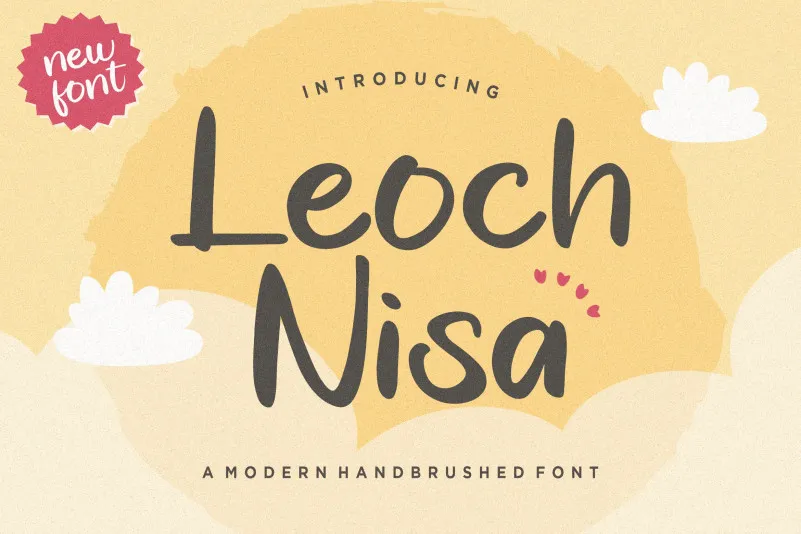
Leoch Nisa Font – Fonte Grátis
Leoch Nisa Font
A Leoch Nisa é uma bela fonte Brush Font que se destaca pela sua elegância moderna e acabamento brincalhão. Ideal para diversos tipos de aplicação, esta fonte pode ser usada com sucesso no design de casamentos, projetos de marca, logotipos, cartazes, cartões de nome, convites, posts em redes sociais, e muito mais. Com uma aparência sofisticada que mistura modernidade com um toque de naturalidade, a Leoch Nisa traz para seus trabalhos um toque único e chamativo. Seja você um designer de casamentos buscando algo novo e criativo para suas designs, ou simplesmente alguém que está procurando uma fonte divertida e elegante para seus projetos em geral – é certamente o tipo de font que você precisa. Suavemente branca sobre qualquer fundo, esta font permite que seus trabalhos tenham um aspecto único que se destaca do resto. A Leoch Nisa é a escolha perfeita para quem procura uma fonte moderna e charmosa para suas próximas criações visuais, sem perder seu toque pessoal e criativo.